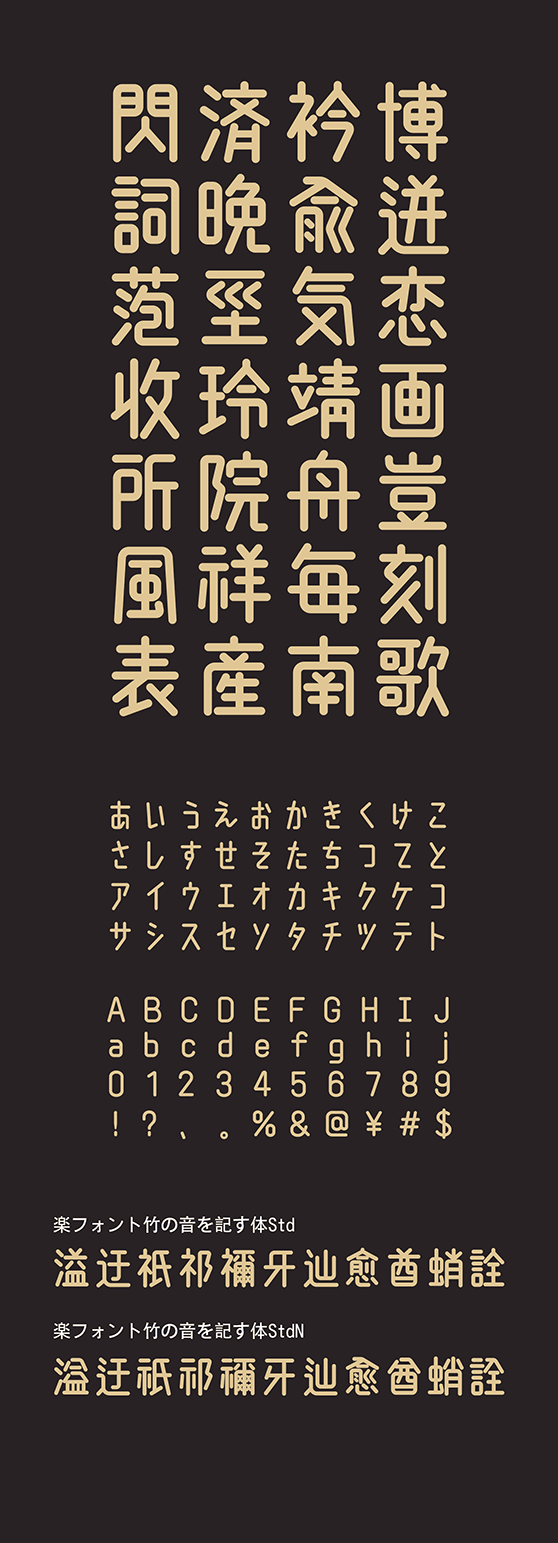
楽フォント
竹の音を記す体 (たけのおとをしるすたい Std・StdN同梱)
TakenootooshirusutaiStd, TakenootooshirusutaiStdN
竹筆のように細くやわらかなストロークと、軽やかな手書きのリズムが生み出す、やさしく親しみやすい表情のフォントです。丸みのある形と心地よい余白が読みやすさを高め、日常文やエッセイ風のレイアウト、ヒーリング系、SNS など、柔らかい雰囲気を伝えたい場面に最適です。